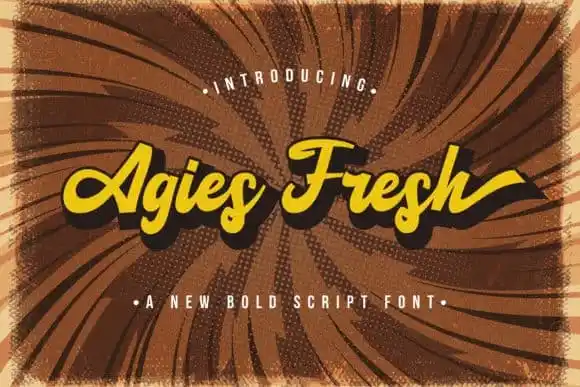
Agies Fresh Script Font – Fonte Grátis
Agies Fresh Script Font
Olá! Estou aqui uma nova fonte script para seu uso em projetos digitais que certamente irá dar destaque à sua identidade visual. Intitulada Agies Fresh Script Font, é um tipo vintage bold inspirado no estilo moderno e retro, feito pelo designer StringLabs da 99designs. Este texto suave e arredondado, perfeito para marcasar uma marca, pode ser usado em um vasto número de projetos. Ele se adequa bem a logotipos, identidades de produtos ou tags, embalagens, headlines, cartazes, camisetas, cards de saudação e até mesmo convites para casamento. Com suas linhas curvadas e arredondadas, a Agies Fresh Script Font oferece uma pegada vintage única que se adapta perfeitamente aos estilos modernos. Sem dúvidas, é uma ótima escolha para quem está em busca de algo diferente e elegante ao mesmo tempo. Dê uma olhada nessa fonte versátil e atemporal para dar um toque especial aos seus projetos digitais!